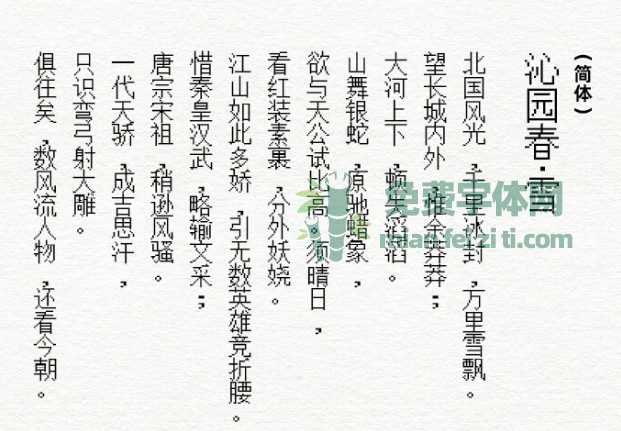
之前免费字体网介绍过一款中文像素字体给大家,受到大家的欢迎。 中文像素字体是GB2312的字符集,具有6000多个常用中文字。
Unifont点阵黑是一个Unicode字体,每一个可见的Unicode基本多语种平面代码点都有一个字形,具有修改字体的支持实用程序。Unicode基本多语言平面覆盖第一个65,536(或2^16)Unicode代码点。最新版本的Unifont包含超过5.5万个符号,涵盖所有可见的Unicode BMP代码点。其中,近二万八千字是中日韩(Cjk)的表意文字。如果你想拥有更多的文字,比如想使用繁体字、韩文等,建议你下载Unifont点阵黑。
Unifont点阵黑与中文像素字体在字体的设计上很相似,但实际细节上有很多的不同。中文像素字体笔画上带有衬线,更像宋体。Unifont点阵黑则没有衬线,更像黑体。它们在英文字符的设计上也有所不同。